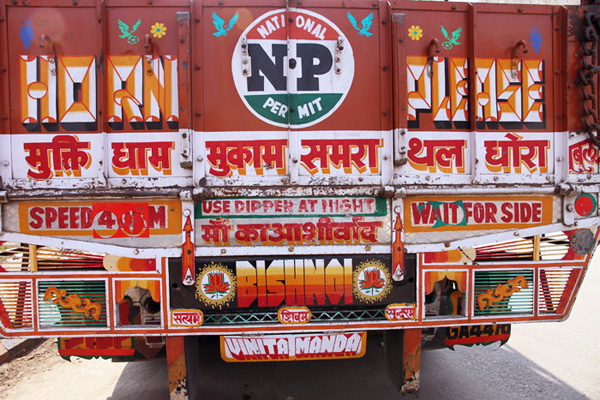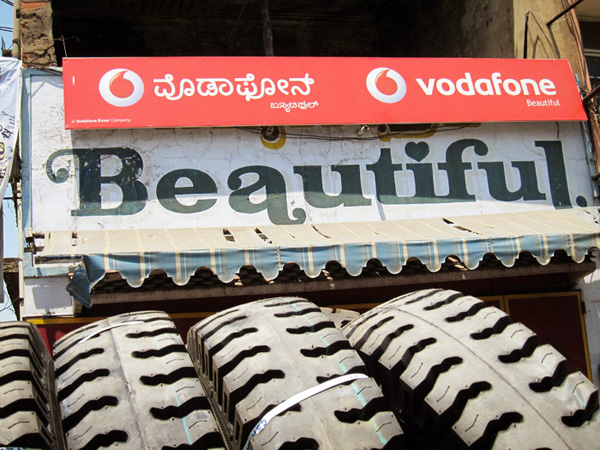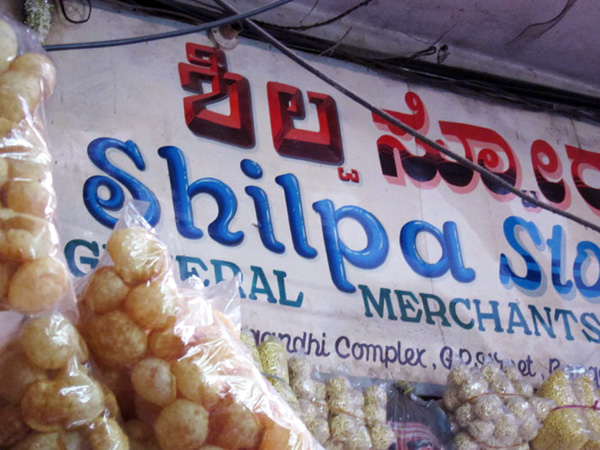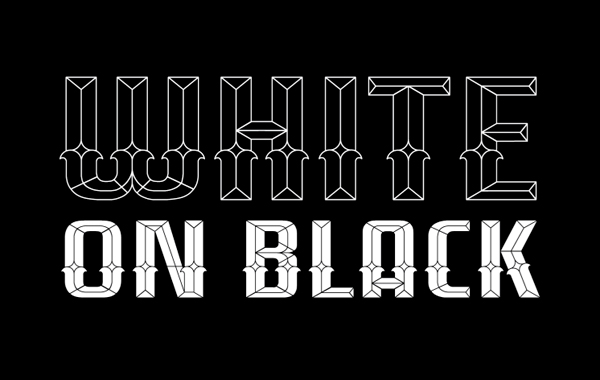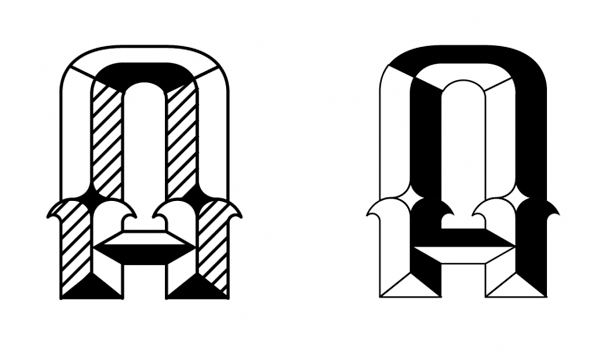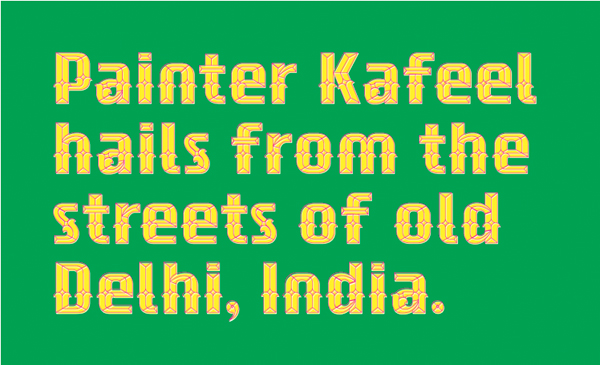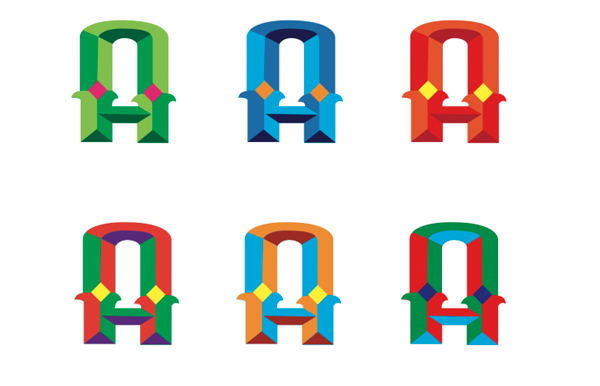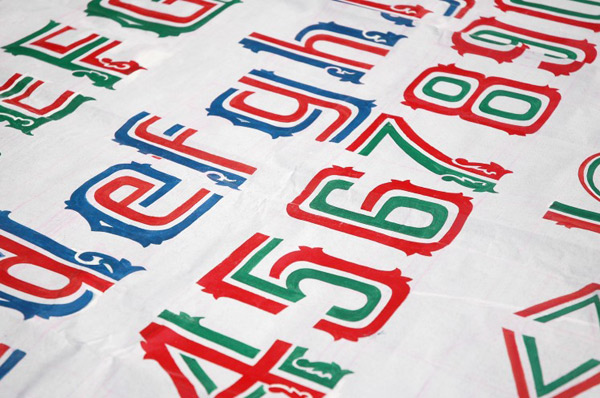
HandpaintedType, proyecto para rescatar la tipografía de la India
Poco a poco, los viejos carteles pintados a mano que caracterizaban muchos de los comercios de la India están siendo sustituidos por los nuevos diseños en vinilo, considerablemente más rápidos y baratos de producir. Para evitar su desaparición total, el diseñador hindú Hanif Kureshi ha lanzado HandpaintedType, un proyecto colaborativo que aspira a rescatar del olvido el trabajo de cientos de cartelistas y tipógrafos callejeros.
Camión decorado con diseño tipográfico, 2011.
El empuje de las nuevas tecnologías ha convertido al cartelista en una especie en extinción: el pincel está hoy condenado a perder la batalla frente al ordenador, mucho más rápido y barato a la hora de producir letreros y rótulos. Más allá del inevitable cambio, la veloz transición entre lo analógico y lo digital corre el riesgo de sepultar en el olvido el trabajo y las técnicas de cientos de artistas gráficos.
Rótulo comercial de la India, 2011.
Hanif Kureshi, tipógrafo establecido en Nueva Dheli, lidera un proyecto dedicado a documentar y digitalizar la obra de los cartelistas y rotulistas de la India. “Es importante preservar esta forma de arte para que las futuras generaciones la puedan comprender y apreciar”, apunta el diseñador.
Rótulo comercial de la India, 2011.
El proyecto aboga por la colaboración popular para involucrar al máximo de cartelistas: por ello, se pide a los hindúes que localicen los rótulos pintados de su barrio y contacten con su diseñador a través del nombre y número de teléfono, normalmente situado en el extremo inferior derecho del cartel.
Tela con tipografía Kafeel, 2011.
Letra A con tipografía Kafeel, 2011.
Texto en blanco y negro con tipografía Kafeel, 2011.
Texto en colores con tipografía Kafeel, 2011.
Texto con tipografía Kafeel, 2011.
Detalle de la tipografía Kafeel, 2011.
Método de composición de la letra A, tipografía Kafeer, 2011.
Diferentes pruebas de la letra A, tipografía Kafeer, 2011.
Una vez contactado, el autor escribe el alfabeto latino, cifras y símbolos incuídos, sobre una superficie de tela de 1x2,5 metros. Finalmente, el tejido es enviado por correo a Kureshi, que se encarga de reembolsar a posteriori el precio cobrado por el pintor, normalmente entre trescientas y quinientas rupias (de tres a siete euros).
Segunda tipografía de Kafeeer, Kafeer, 2011.
Detalla de la segunda tipografía de Kafeeer, Kafeer, 2011.
Tela con tipografía Umesh, Umesh, 2011.
Detalle de la tipografía Umesh, Umesh, 2011.
Tela con tipografía Vaghela, 2011.
Detalle de tipografía Vaghela, 2011.
Tela con tipografía Vasant, 2011.
Detalle de tipografía Vasant, 2011.
Tela con tipografía Bindra, 2011.
Detalle de tipografía Bindra, 2011.
Detalle de tipografía Shakeel, 2011.
Posteriormente, los caracteres de las telas son analizados por el propio Kureshi y el diseñador tipográfico Sarang Kulkarni. Las letras de los carteles son reconvertidas en tipos digitales que pueden ser compradas en Internet. La mitad del beneficio obtenido por cada venta le corresponde al autor.